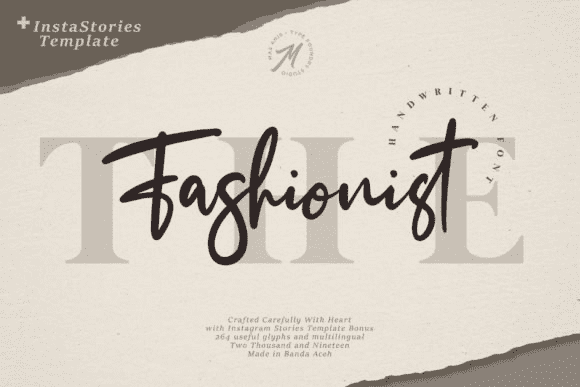
Название: The Fashionist Font (2021)
The Fashionist - это повседневный фирменный шрифт с изысканными акцентами.
Он включает полный набор великолепных прописных и строчных букв, цифр, большой выбор знаков препинания и лигатур, а также бонусные шаблоны Instagram Story!